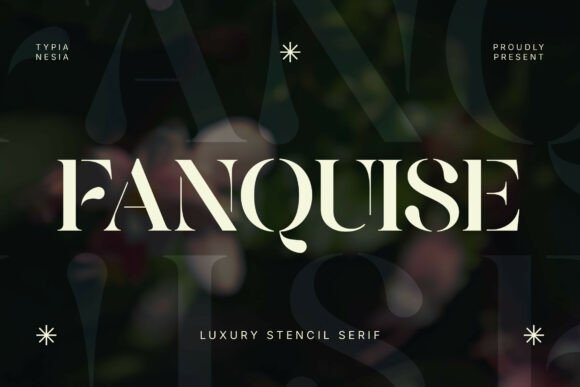
Fanquise
Trovare i giusti elementi di design può essere difficile, ma Fanquise offre una collezione eccezionale che eleva istantaneamente il tuo lavoro.
Realizzato con precisione, Fanquise fornisce vettori puliti, tipografia fluida e una licenza commerciale per la massima tranquillità.